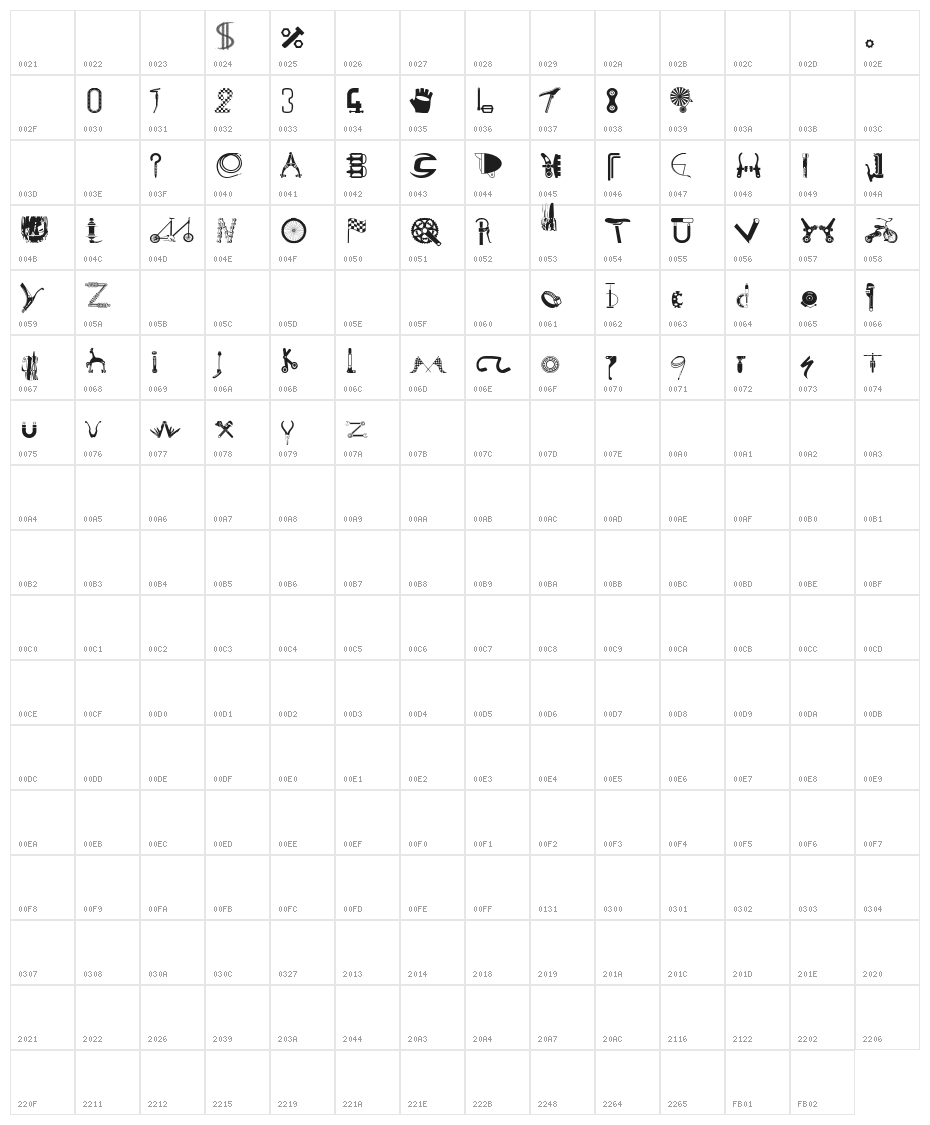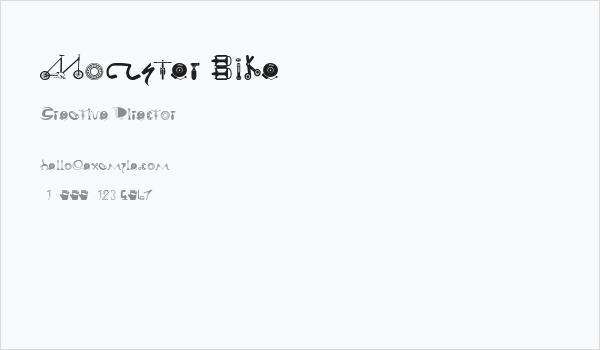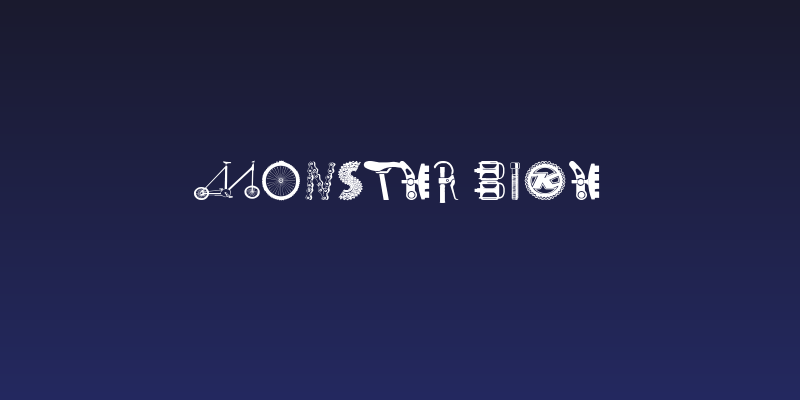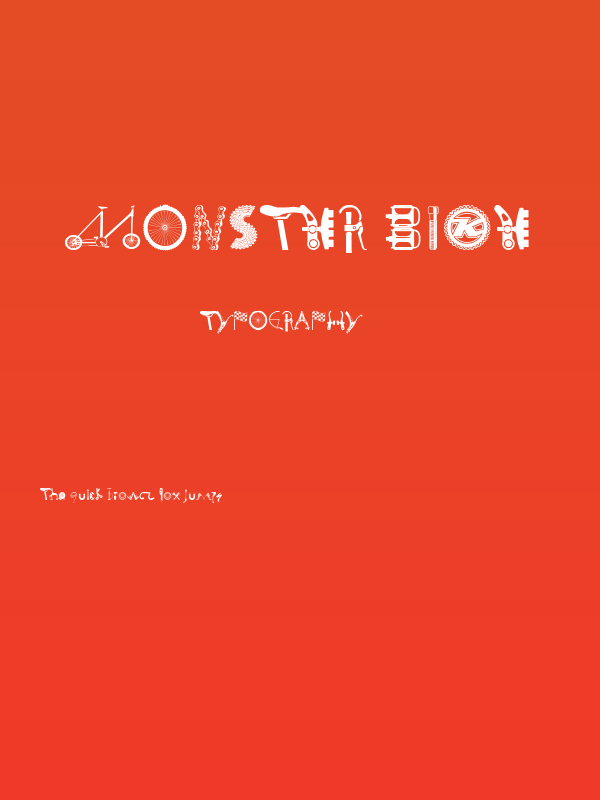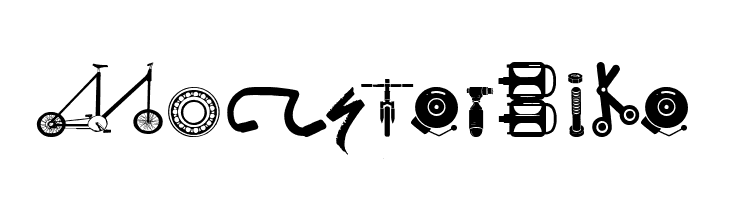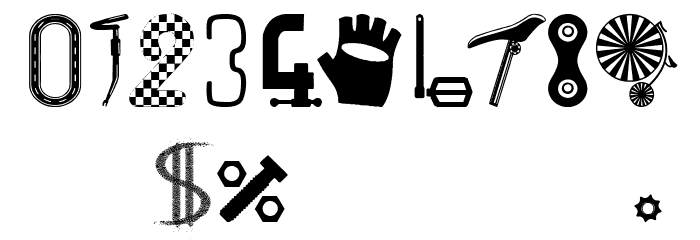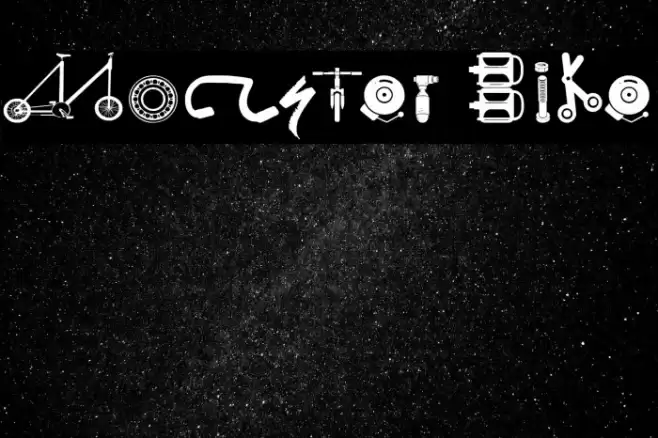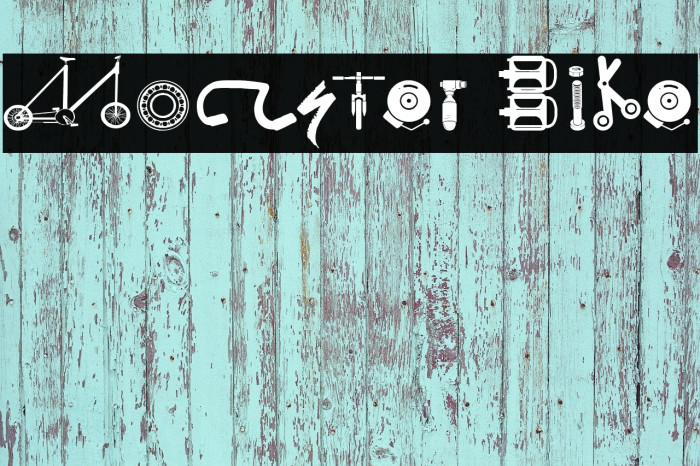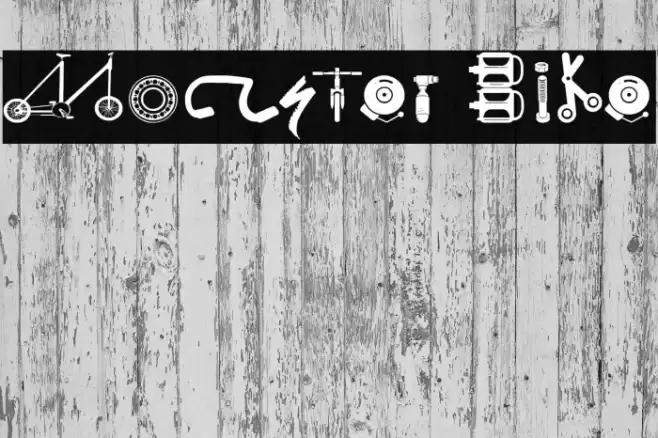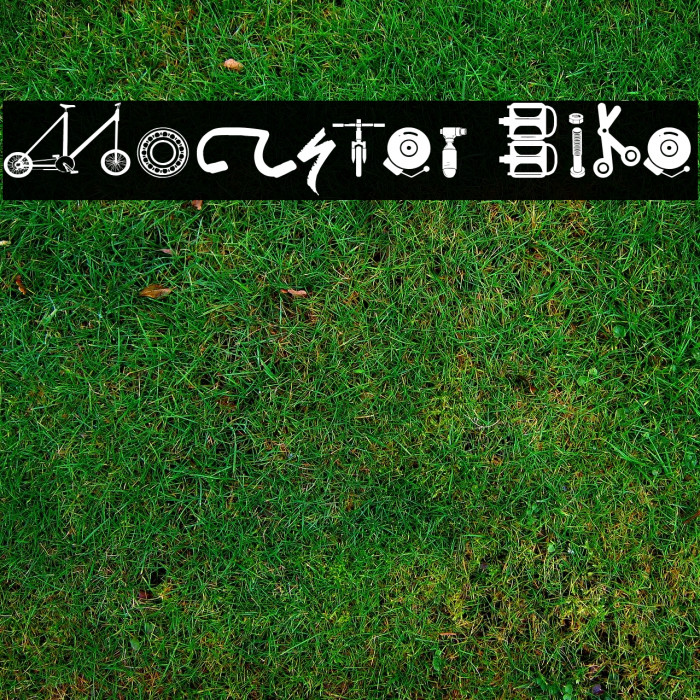
Monster Bike Font
| Proyectos propuestos | This font is perfect for projects related to cycling events, bike shop branding, mechanical workshops, or any creative project that benefits from a playful, industrial theme. |